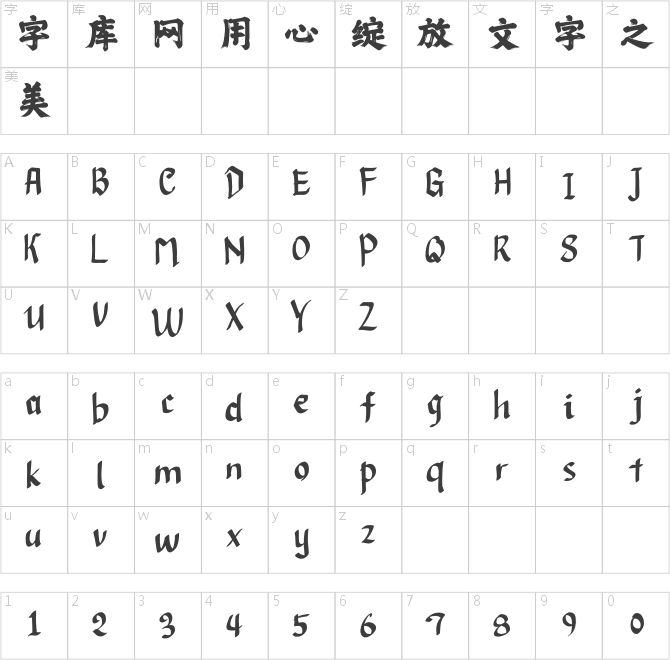
漢儀新蒂佛塔書字體下載HanyiSentyPagoda
漢儀新蒂佛塔書是一款綜合了歷代匾額,特別是佛教古塔古跡書法特征的一款字體。設(shè)計師通過嚴謹?shù)姆治黾霸賱?chuàng)作,再現(xiàn)了大楷墨跡書寫的蒼勁氣勢、以及莊嚴雄壯的佛教古跡書寫風格。該字體適用于國風文化類的設(shè)計環(huán)境。